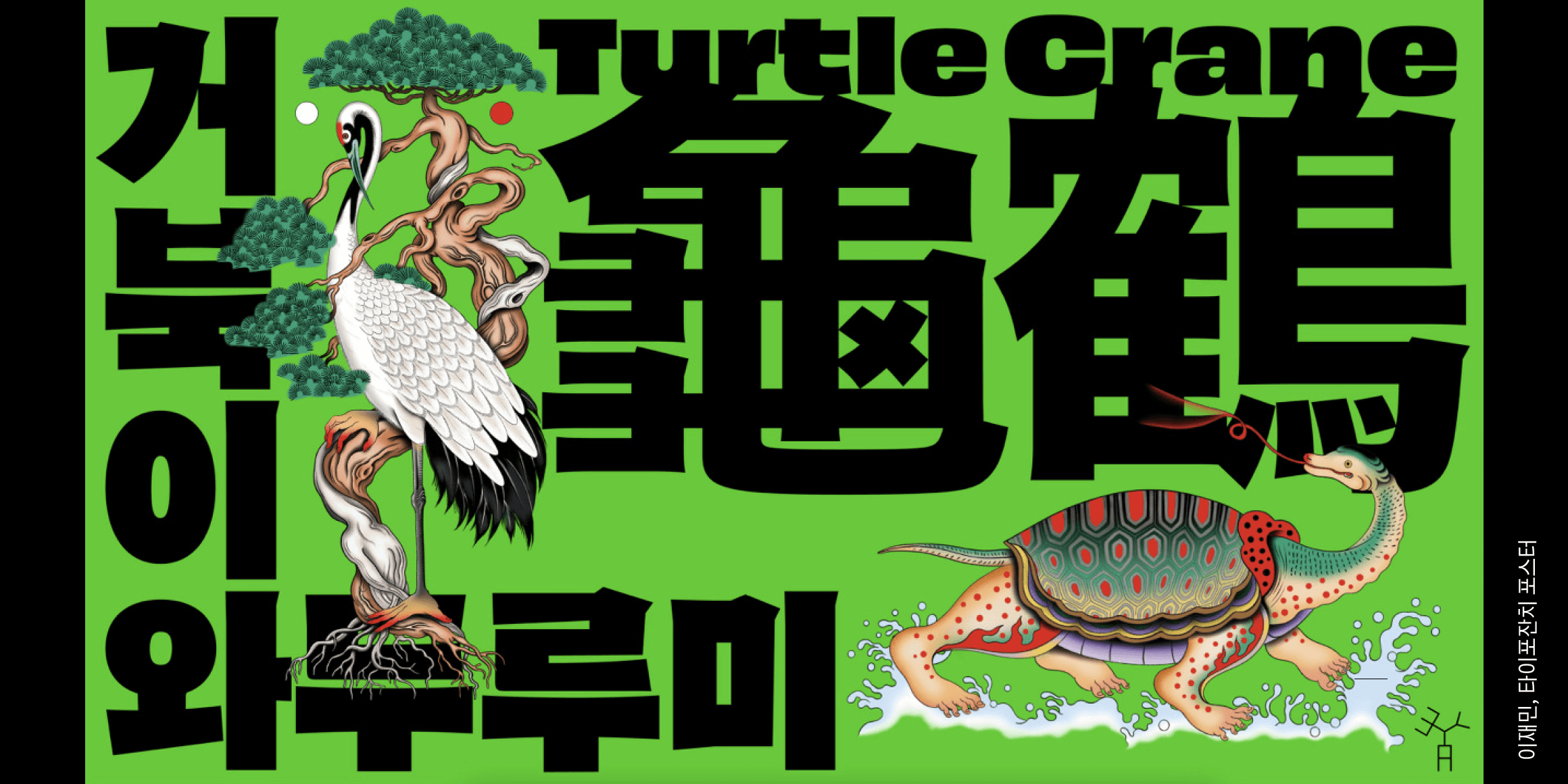
2022년 첫 출시부터 많은 사랑을 받아온 쥬키니 패밀리 시리즈 중 하나인데요, 이번에는 어떤 모습의 쥬키니로 등장했을까요.
쥬키니 가족구성
패밀리이지만 각각의 서체마다 개성 강하고 매력 있는 쥬키니 가족.
쥬키니는 일반적인 패밀리와는 개념이 조금 다릅니다. 가장 굵은 굵기의 헤비 타이틀용으로만 구성된 패밀리로서 2022년 출시된 쥬키니를 첫 시작으로 꾸준히 가족을 확대하고 있습니다. 획대비와 지읒, 치읓과 시옷의 자소 비대칭, 기억과 키읔의 과감한 사선 획은 패밀리로 유지하되 하나하나의 폰트가 다른 획의 디테일을 가지며 다양한 인상을 표현하는 역동적이며 유니크한 패밀리 구성입니다.
쥬키니의 오목한 획과 자소의 비대칭은 유지하며 길쭉한 쥬키니만의 특징으로 장체와 자소(ㄴ,ㄷ,ㅌ,ㄹ)의 가로획 사선 처리로 기획.
두 개의 큰 방향 설정 후 우연히 접하게 된 1960년대 사회문화에 영향을 받은 사이키델릭 포스터는 길쭉한 쥬키니의 디자인 디테일을 잡는데 많은 영향을 주었습니다. 사이키델릭 포스터에 종종 등장하는 메세지를 전달하는 도구로 사용된 글자 형태는 장체에 오목한 획 그리고 다소 왜곡된 곡선과 획으로 표현된 것을 볼 수 있었고 이를 길쭉한 쥬키니 디자인 특징으로 잡으면 어떨까 하는 상상으로 시안이 시작되었습니다.
Width의 경우 쥬키니는 전각, 길쭉한쥬키니는 618로, 좁아진 가로폭 안에서 가로획과 세로획의 변화가 생기게 됐고 이전 쥬키니 패밀리와는 다른 사이키델릭에서 보여지는 과감한 선과 획에서 주는 디테일을 길쭉한쥬키니의 가로획에 사선 처리를 하여좁아진 가로폭 안에서 생기는 굵기의 불균형과 같은 시각적 문제를 동시에 해결할 수 있었습니다.
한글 디자인에서는 쥬키니 패밀리로서 사이키델릭 컨셉에 충실하게 표현된 문장부호 추가 글립이 있으니 확인해주세요.
옵티컬하고 날카로운 선으로 조금의 그로테스크한 요소가 돋보이는 문장부호를 함께 사용해보세요.